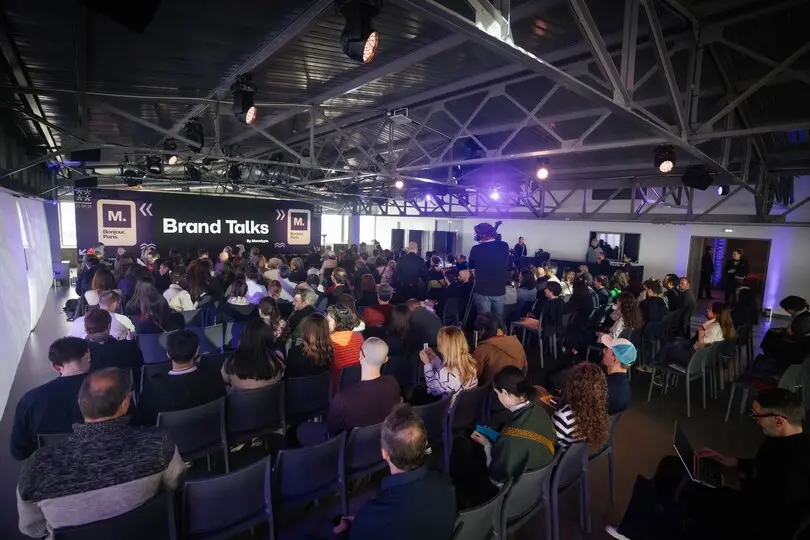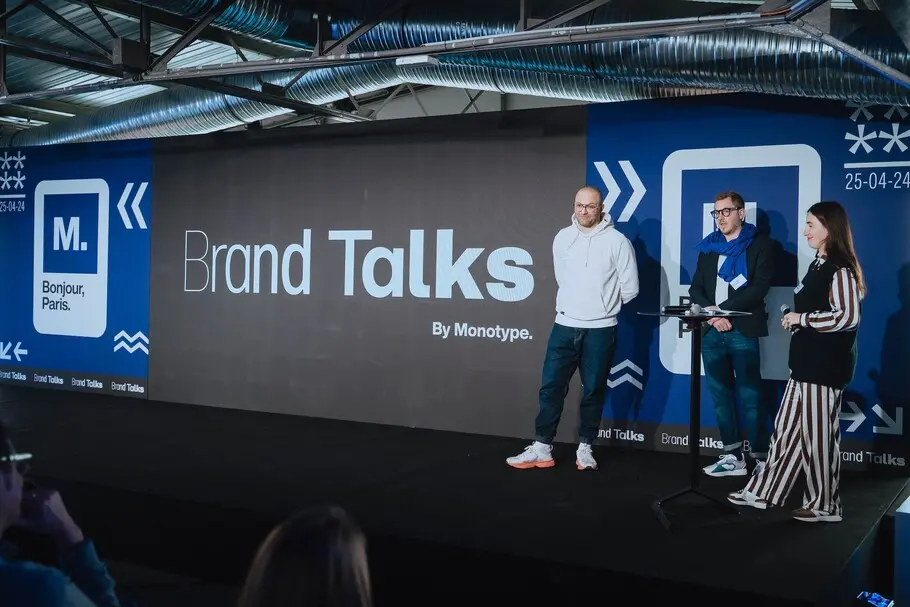
Brand Talks Paris
Nous avons récemment eu le plaisir d'organiser un événement Brand Talks à Paris. Il s’agissait de la deuxième édition de Brand Talks dans la capitale et nous sommes ravis de partager qu’elle a été couronnée de succès ! C’est dans un lieu d’exception, avec des vues à 180° sur les toits de Paris, que nous avons passé un après-midi des plus fascinants à écouter ce qui se fait de mieux dans le design. Renaud Cambuzat, de la marque de lingerie Chantelle, a ouvert le bal avec une présentation centrée sur la restructuration dans un marché en pleine évolution. Ensuite, Reza Bassiri, de l'agence de design Carré Noir, accompagné d'Isabelle Duvernay (de la banque CCF), a présenté deux études de cas : la renaissance de la banque française patrimoniale CCF et le récent rebranding des brasseries Kronenbourg. Alexandre Delassus et Pascal D’Amico ont suivi avec une présentation axée sur la nouvelle identité de la méga-marque de sport Decathlon. Damien Collot et Laurène Girbal, de Monotype, ont clôturé l’après-midi avec un hommage poétique à la typographie.
Lisez la suite pour découvrir les cinq points forts de Brand Talks Paris 2024:
1. L’adaptabilité et l’innovation au premier plan
Dans marché en pleine évolution les demandes et dynamiques des consommateurs changent et évoluent en permanence. Ainsi, pour rester pertinentes, les marques doivent s’adapter, et les récentes transformations de Chantelle et de Decathlon en témoignent. Le repositionnement audacieux de Chantelle visait à « offrir de nouvelles propositions, en ligne avec les défis de l’époque, et à contribuer à la transformation de notre industrie et de ses codes ». Chantelle a relevé le défi d’un marché en mutation tout en restant fidèle à son héritage. Cet engagement pour l’innovation a permis à la marque d’anticiper de nouvelles tendances tout en capitalisant sur son nom pour stimuler sa croissance. En effet, avec Chantelle Lab, le groupe confirme ses engagements en offrant des solutions innovantes aux besoins changeants des consommateurs : la société propose, par exemple, la première ligne de lingerie 100 % recyclable.
De la même manière, la nouvelle identité de Decathlon témoigne des ambitions du groupe pour une identité de marque unifiée sur le plan international, articulant son message dans tous les marchés où elle est présente autour d’un slogan uni, « Ready to play? », en anglais, partout.
2. Un accent sur l’identité de marque
Un autre aspect central aux présentations de Brand Talks Paris était la volonté, et même la nécessité, pour une identité de marque claire et unifiée. Nous avons découvert des marques complexes et diverses voulant simplifier leur structure pour une plus grande clarté et reconnaissabilité. À titre d’exemple, la nouvelle identité visuelle de Decathlon s’accompagne d’une nouvelle stratégie de marque, visant à faire passer son image d’un distributeur d’équipements sportifs à une marque de sport globale et unifiée. Unifiant, pour la première fois de son histoire, sous un même nom et un même logo, son vaste portefeuille de marques spécialisées. Le besoin de restructurer Chantelle, amené par différents phénomènes, suit cette même tendance. Un désir marqué de « Restructurer notre écosystème de marques pour gagner en clarté́, efficacité́ et visibilité́ », passant d’une marque historique à une marque pleinement moderne, engagée et innovante. Semblable à Decathlon, la simplification de marques spécialisées sous un même chapeau était au cœur de la transformation de Chantelle. Il en va de même pour CCF. La banque a une histoire quelque peu surprenante dans le sens où elle existe depuis plus de 100 ans mais a été absente ces 20 dernières années, et bien qu’elle ait réussi à maintenir tout le long une bonne réputation auprès des générations plus âgées, alors qu’elle renait de ses cendres, elle avait besoin d’une identité moderne pour parler aux jeunes.
3. Allier modernité et tradition
Une bonne image de marque traduit un équilibre délicat entre passé et avenir. En utilisant leur héritage comme source d’inspiration et de socle, les marques peuvent naviguer avec confiance et pertinence dans les complexités d’un marché moderne, en s’ouvrant à de nouveaux publics tout en restant reconnaissables et ancrées. Les présentations de Brand Talks sont fidèles à cette idée. La refonte des Brasseries Kronenbourg,par exemple, qui est à la fois totalement moderne et nouvelle, est imprégnée de tradition. Il suffit de regarder leur nouveau logo – indubitablement un blason, un pont héraldique entre passé et présent. Dans le même ordre d’idées, nous avons la promesse de Decathlon selon laquelle ils sont « Still a blue brand » (toujours une marque bleue).
Ils affirment haut et fort que oui ils ont changé, mais ils sont toujours les mêmes, fidèles à leur vision et objectif d’origine. Le logotype de la marque, un élément clé de son identité, a été affiné pour garantir la reconnaissabilité et la polyvalence dans diverses applications. La décision de conserver la connexion entre les lettres C et A symbolise l’héritage et l’évolution de la marque. Le nouveau logo de l’entreprise est également un clin d’œil discret au passé : le logo est une orbite – représentant l’inclusivité et l’accélération – avec une pointe au centre, un rappel aux origines de la marque dans les sports de montagne.
Alexandre Delassus et Pascal D’Amico, Decathlon
4. Branding centré sur l’humain
Un des fils conducteurs des différentes présentations de Brand Talks Paris était un angle très humain. Ce n’est peut-être pas tout à fait surprenant qu’à une époque de changements et d’incertitudes que l’authenticité soit de mise. Nous avons découvert des marques privilégiant l’empathie, la tolérance et la communauté, et se faisant créant des liens durables avec leurs clientèles et se démarquant dans leurs marchés respectifs.
Le nouveau slogan de Decathlon en est une illustration. Ils demandent si nous sommes « Ready to play ? » (prêts à jouer), une question ouverte invitant tout le monde, sans distinction d’âge, de sport de prédilection, ou de niveau de compétence, à prendre part et s’amuser.
Les photos minimalistes qui renforcent la nouvelle identité de Kronenbourg en sont un autre exemple clair. Les photos, montrant des champs d’orge et des cônes de houblon, nous ramènent directement à la terre et aux individus qui la cultivent.
De même, l’engagement de Chantelle à parler à toutes les féminités s’articule à travers les campagnes de la marque. Ils ont été, par exemple, la première marque de lingerie en France à promouvoir l’inclusivité, s’éloignant d’une image statique conditionnée par un regard masculin, offrant à la place de multiples interprétations et possibilités de ce qu’est et peut être un corps.
5. Au cœur des conversations
Une bonne image de marque ouvre la conversation, mais une excellente image la fait perdurer dans le temps. C’est une idée centrale à la récente renaissance de CCF. Carré Noir a retravaillé le logo emblématique de la banque, en conservant son tri-lettrage originel, mais avec une touche originale. Le F prend désormais la forme d’un phylactère – littéralement un vecteur de conversation. Cette forme conversationnelle est réitérée et déclinée pour devenir un socle de l’identité de la banque, un indice visuel pour présenter de nouvelles informations, confirmant ainsi visuellement l’engagement de la banque à dialoguer avec ses clients. Ce F phylactère est associé à des teintes pastels, donnant à la banque une identité totalement unifiée et résolument moderne.